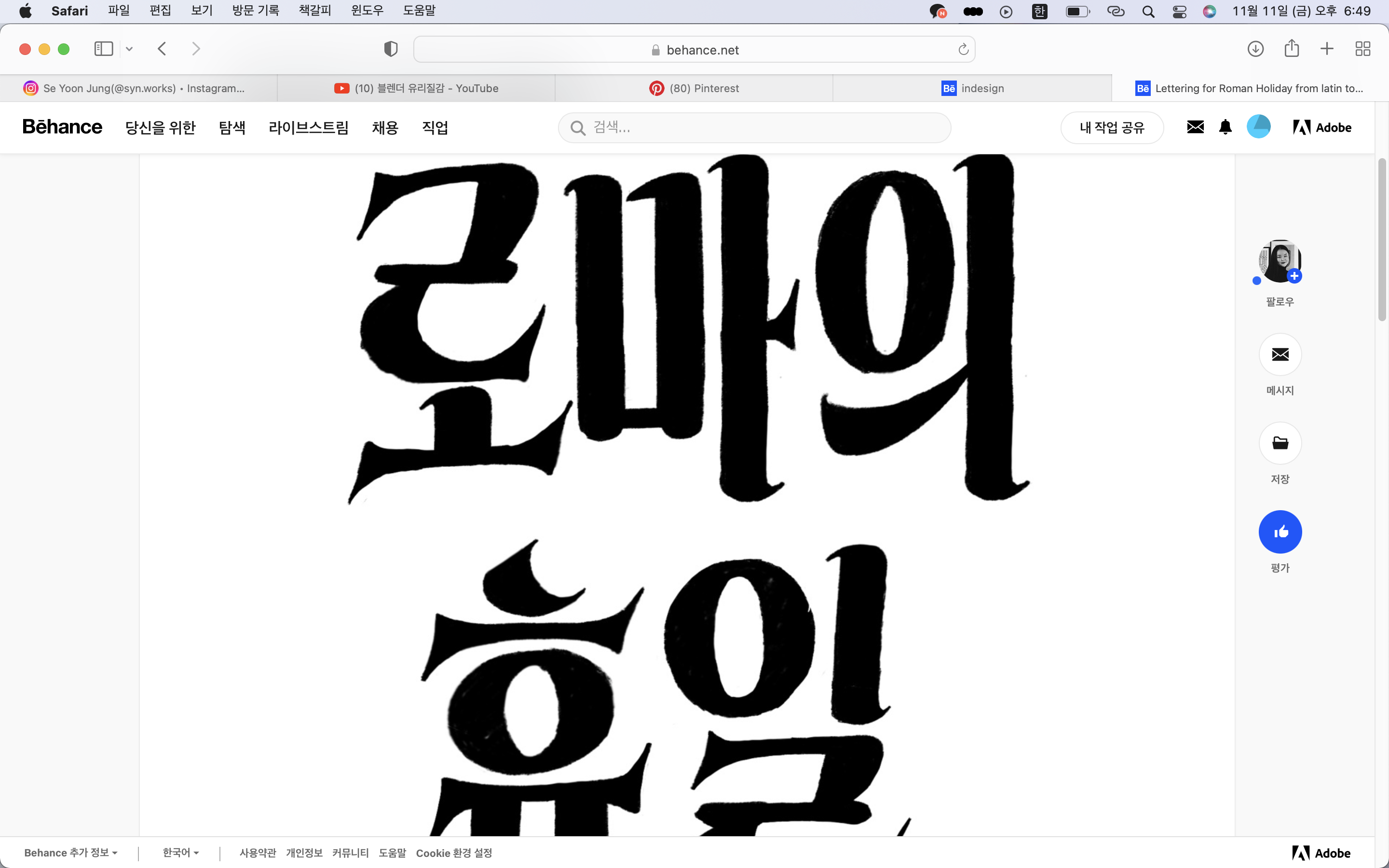
혹시 이서체 무엇인지 알 수 있을까요? par*** 2022.11.11 부탁드립니다. 댓글 0 등록 오타대마왕 폰트가 아닌 라틴을 한글화해서 레터링을 한 거에요. 아마 함민주 디자이너님이 하신거 같아요, 옆에 사진이. ㅎㅎ 2022-11-14 답글 달기 댓글 더보기 쉽고 빠르게 가장 비슷한 폰트를 알고 싶다면? 이미지로 검색하기
폰트가 아닌 라틴을 한글화해서 레터링을 한 거에요. 아마 함민주 디자이너님이 하신거 같아요, 옆에 사진이. ㅎㅎ